今回は、火曜クラスの硬筆展練習作品をご紹介します。練習を重ねる中で少しずつ整っていく文字や、それぞれの頑張りが感じられる作品がそろいました。どうぞごゆっくりご覧ください。
火曜日 2年生
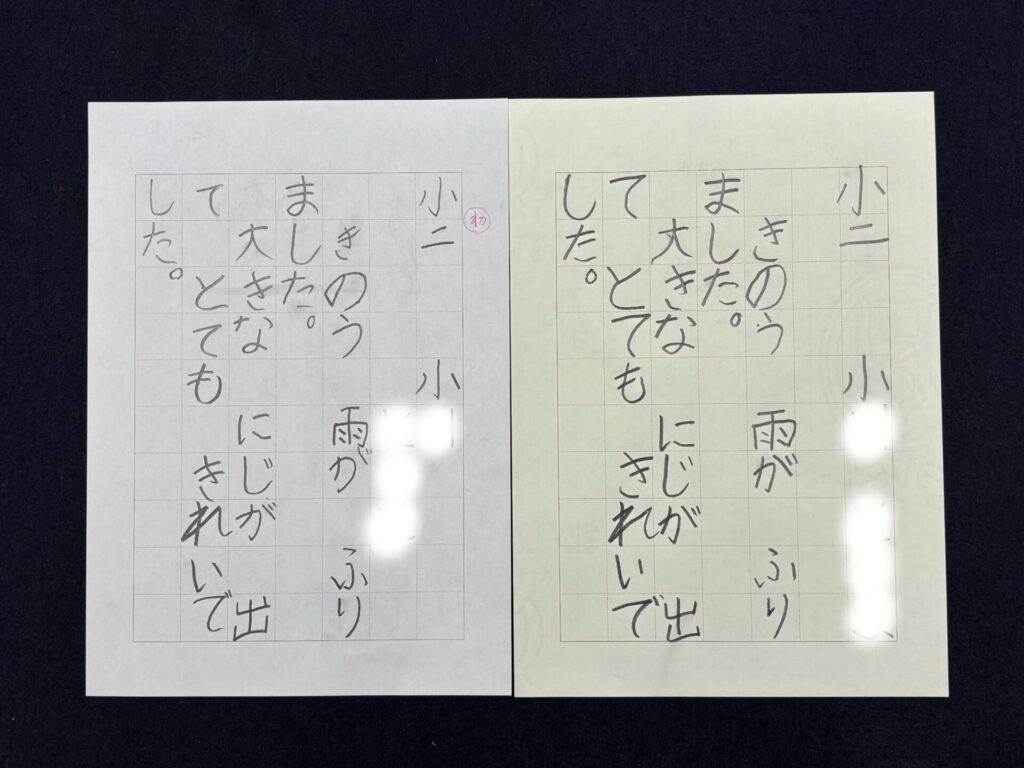
一本一本の線がしっかりして、文字全体の形がきれいに整いました。名前を一生懸命練習していました。マスの中心を意識しながら、のびのびと書けているのが伝わる作品です。
火曜日 1年生
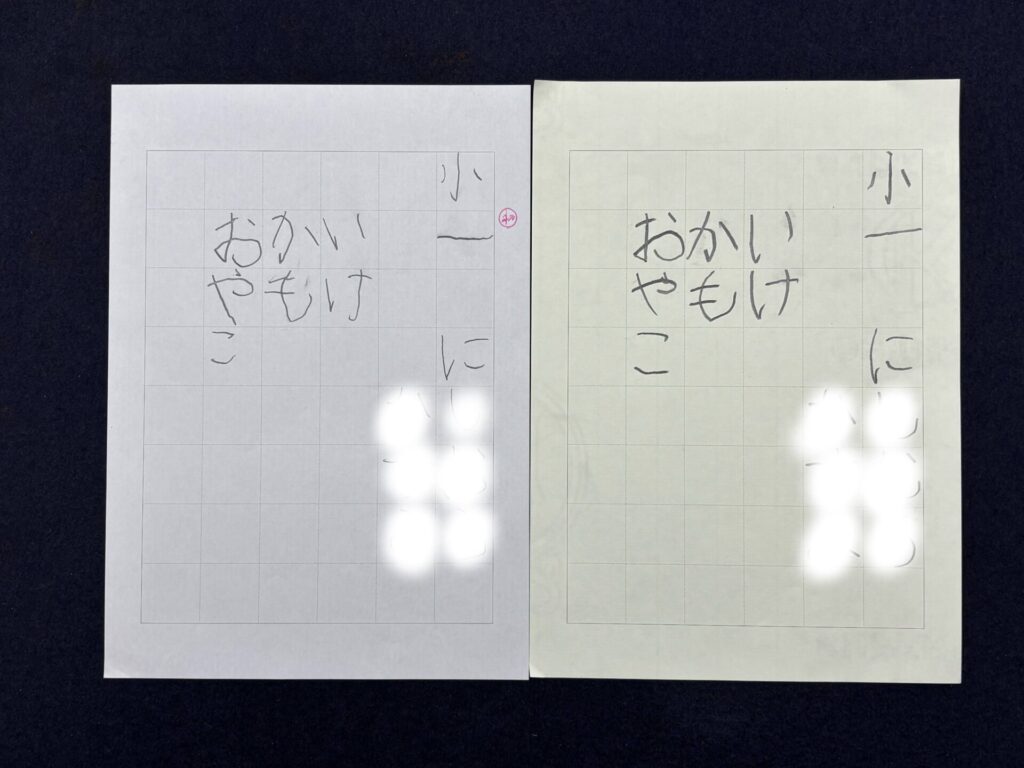
初めての硬筆展の練習でした。のびのびとした線の力強さが出ていて、文字の形がぐんと整いました。ひらがなのやわらかい表情もよく出ていて、マスの中でバランスよく書こうとする頑張りが伝わる作品です。
火曜日 5年生
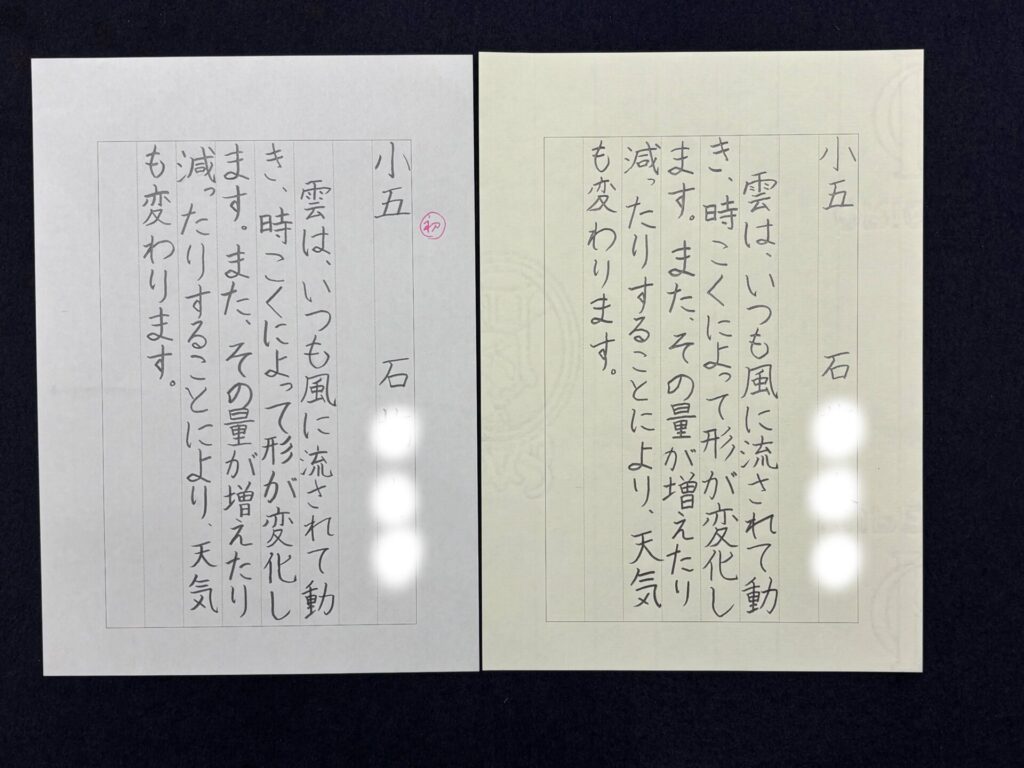
線の太さや濃さに安定感が出て、文字全体がぐっと引き締まりました。漢字とひらがなの大きさの違いも意識できていて、行の流れが美しくまとまった作品に仕上がりました。
火曜日 5年生
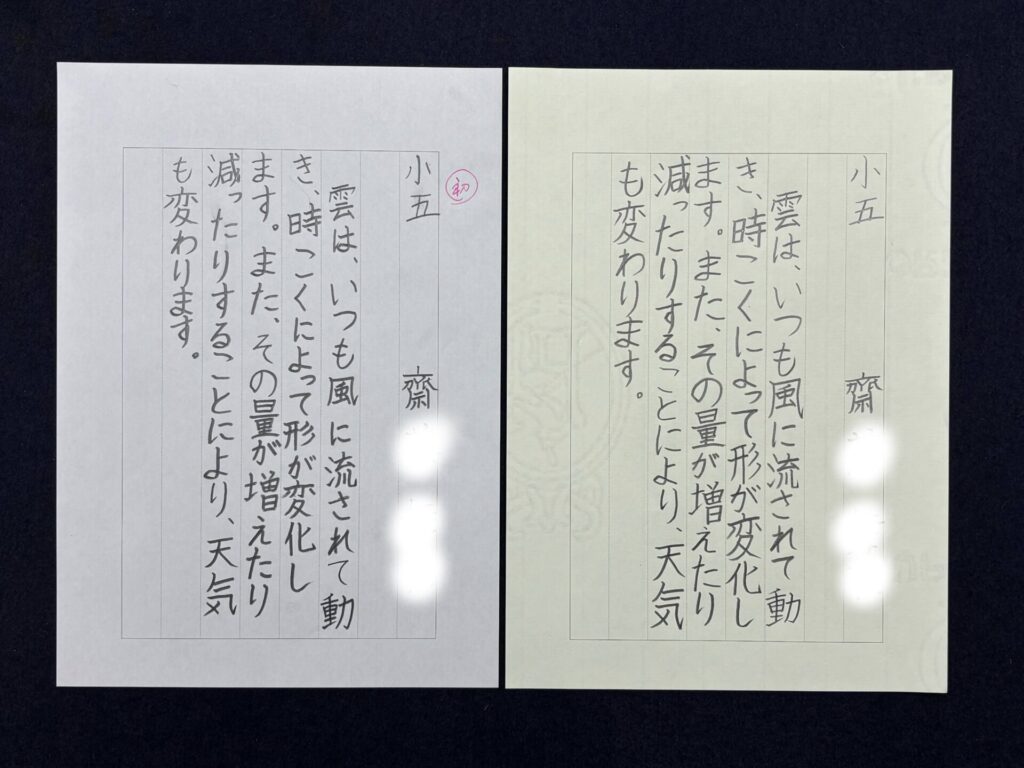
一文字ずつの形がよく整い、字間や大きさのバランスもそろってきました。線の安定感が増したことで、行の流れがすっきりと見える、読みやすい作品に仕上がっています。名前も、時間をかけて練習した成果が出ています。
火曜日 5年生
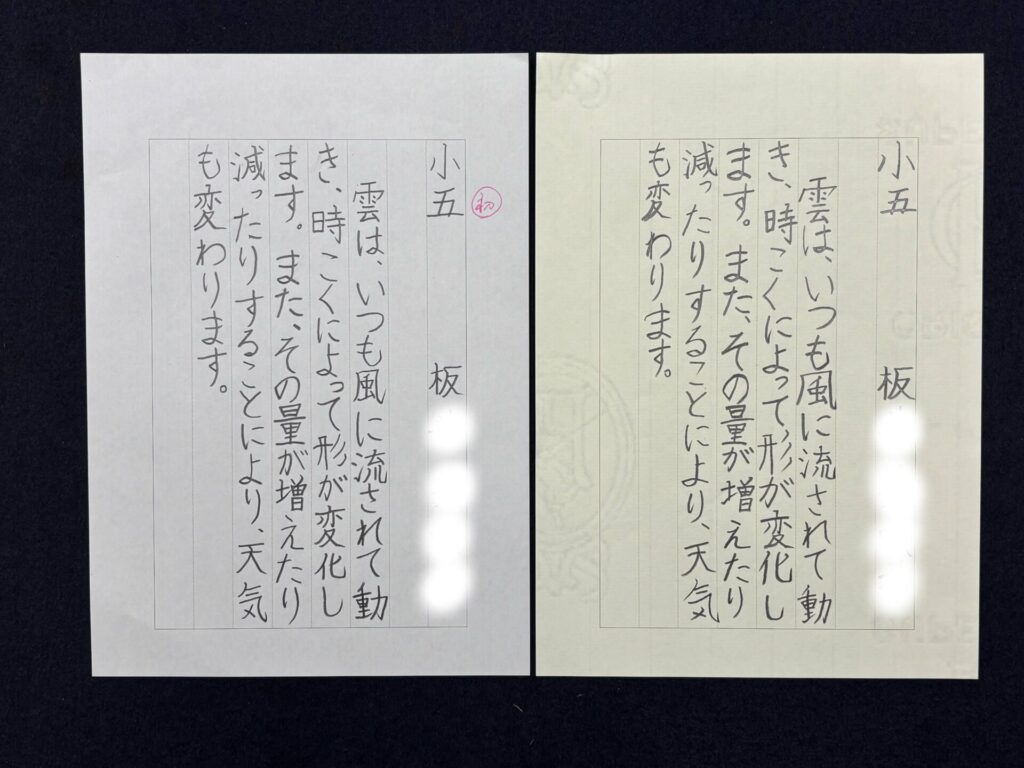
一本一本の線がしっかりして、最初の作品と比べると力強さの表れた清書になりました。漢字とひらがなのバランスを意識して丁寧に書こうとする気持ちがよく表れています。
火曜日 6年生
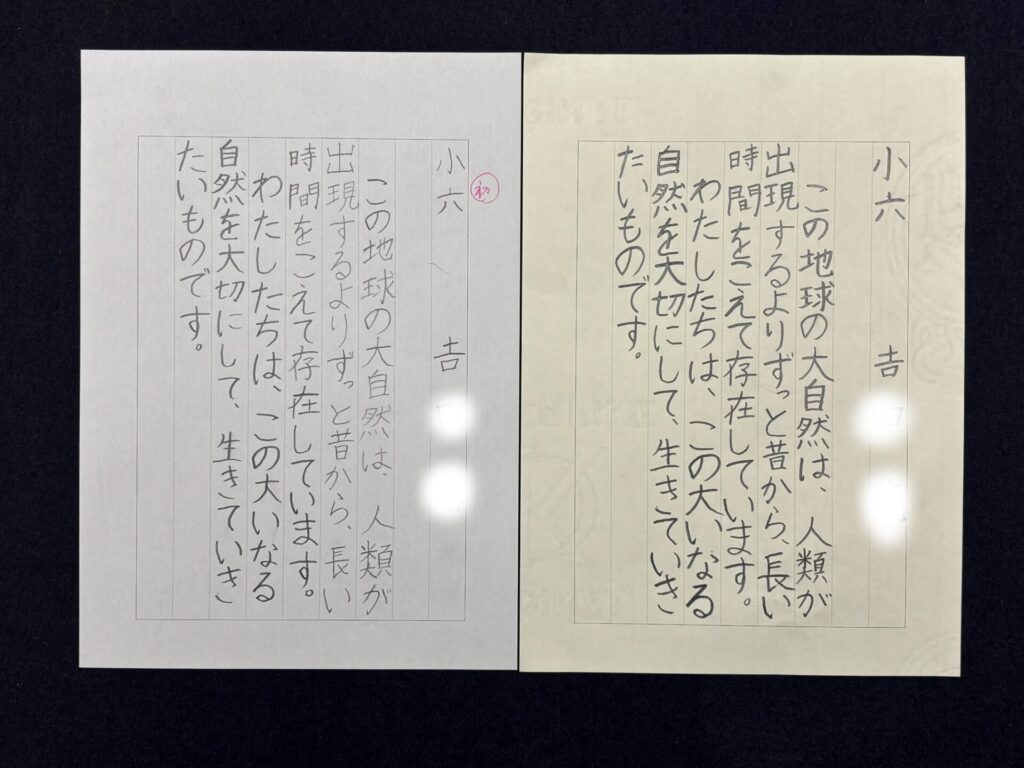
文字の大きさがよくそろい、全体がきりっと引き締まった印象になりました。線の太さや濃さの安定感も増して、行の流れがまっすぐ整い、最後まで読みやすい作品に仕上がっています。
どの作品にも、それぞれの頑張りと成長が感じられる、あたたかいギャラリーとなりました。くり返し練習する中で、文字が少しずつ整っていく様子はとても頼もしく、最後までていねいに書こうとする気持ちがしっかり伝わってきます。火曜日クラスのみなさん、よく頑張りました。